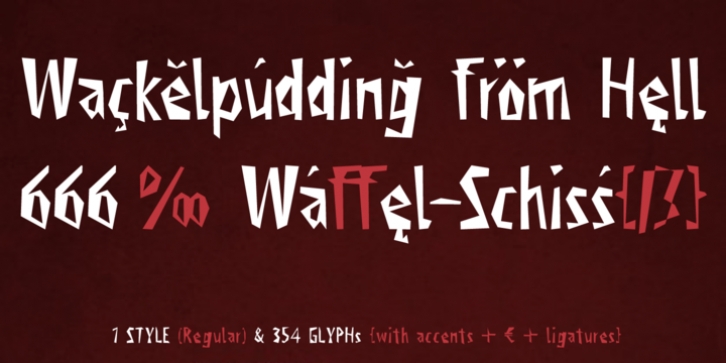
KONZEPT/BESONDERHEITEN Der düstere und markante Charakter dieser Schrift schafft eine sehr individuelle Atmosphäre. Die Buchstabenform erinnert an Äste eines Baumes. Alte, morsche und gebrochene Baumäste. Teilweise erinnern die kantigen Formen an Dornen (Büsche) einer Rose.
EINSATZGEBIETE Die kantige, kontrastreiche Horror und Fantasy Schrift »Viktors Littl Creepy Horror« würde sich über folgenden Einsatz freuen: Überschriften in Zeitschriften oder Webseiten, Filmplakate, Musik Cover oder Webbanner usw.
TECHNISCHE INFORMATIONEN Head­line Font | Dis­play Font | Horror Helloween Font »Viktors Littl Creepy Horror« Open­Type Font (Mac + Pc) mit 354 Gly­phen – alter­na­tive Buch­sta­ben und Ligaturen (dia­kri­ti­sches Zei­chen & €) & 1 Schriftschnitt (Regular)